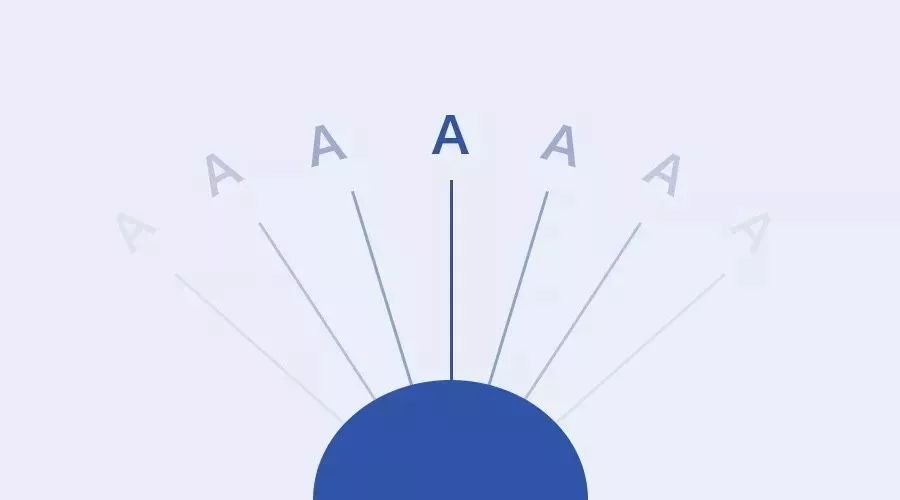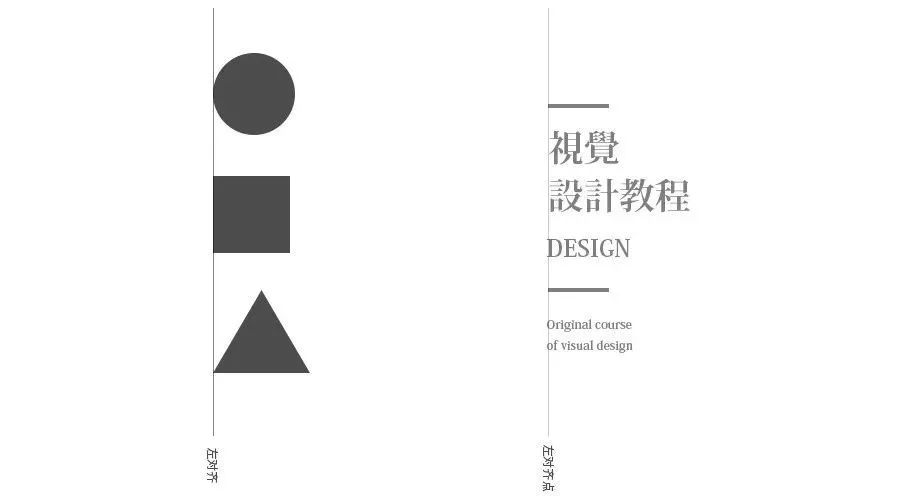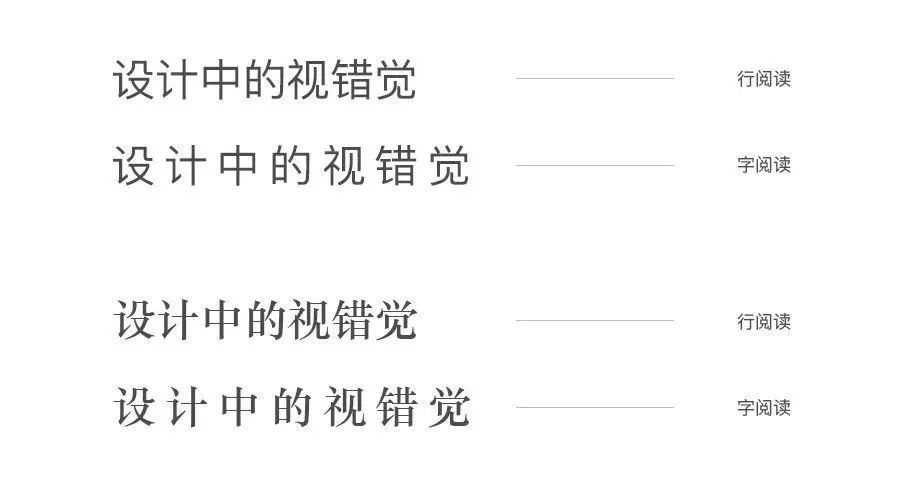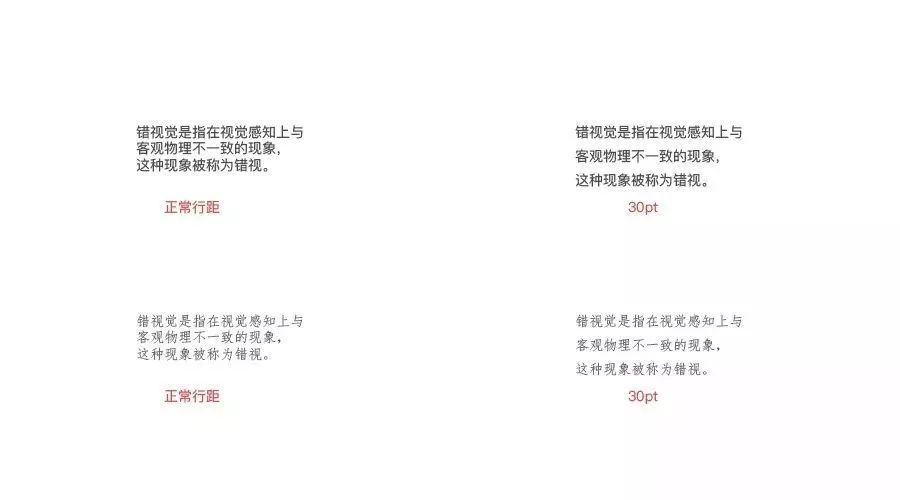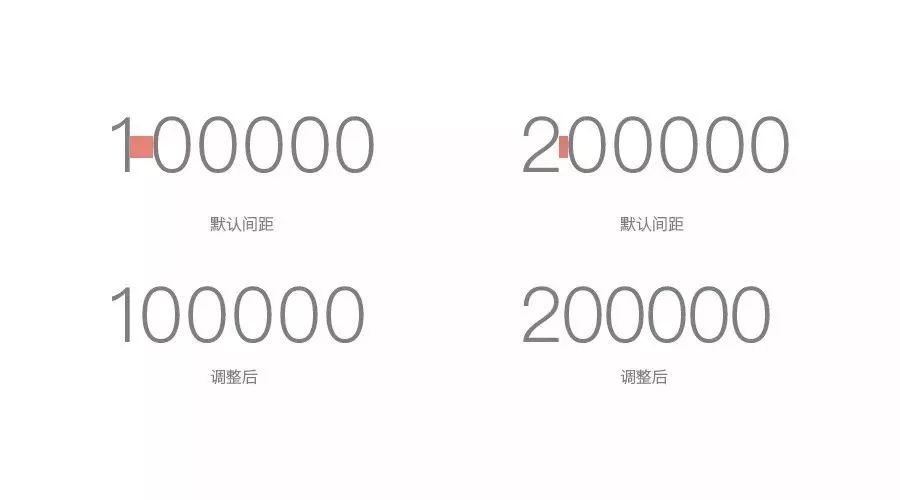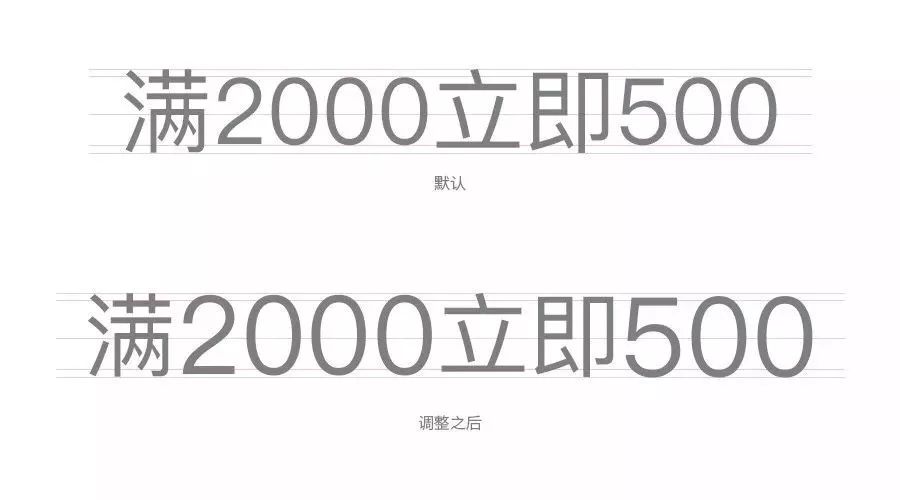
版式设计和字体设计中的人眼视错觉
什么是视错觉
视错觉是指在视觉感知上与客观物理不一致的现象,这种现象被称为错视。人的大脑在接受视觉系统传递而来的信息后,经过综合地进行对比和分析,会尽可能地做出正确的判断,但是,当信息不够充足或者错误收到干扰时,就会出现视觉上的形态与客观物理上的形态不一致的现象,也就会产生视错觉。
如图所示,正常情况下人眼对所看到事物的呈现,当人眼直视正前方的时候,只有中间位置的是最清楚的,而两边则是相对模糊的,同时也比较容易产生视错觉,而视错觉的原因除来自客观刺激本身特点的影响外,还有观察者生理上和心理上的原因。在设计中最常见的就是视觉方面的错觉,而错视觉对版式,字体的大小,间距等等都会有影响。
视错觉就是当人或动物观察物体时,基于经验主义或不当的参照形成的错误的判断和感知。在生活中我们也经常会见到一些视错觉的现象,而这些经典的视错觉也会经常被设计师应用到设计当中。
左边中间的线段与右边中间的线段是等长的,但看起来左边中间的线段比右边的要长,也称为缪勒—莱依尔(Müller Lyer)错觉。其原理是因为两边符号的方向变化,当两个符号的方向发生变化时,其视觉也会随之发生变化。
垂直线与水平线是等长的,但看起来垂直线比水平线长,也称为菲克(Fick)错觉;从视觉角度来讲时因为人眼的视觉中心点在竖线中间的位置,而横竖链接处容易给人一种一分为二的错觉,故在视觉感知上会认为竖比横线长。
中间的两个圆面积相等,但看起来左边中间的圆大于右边中间的圆;称为艾宾浩(Ebbinghaus)错觉。其原理是因为有不当的参照导致视觉感觉偏差,中心圆虽然是相同的大小,但由于外围参照物的对比,使得人眼在感知的时候发生了错觉。
在字体设计中,笔画通常会给我们这样三种不同的视觉感受,对于字体高级阶段来说,要尽可能的避免这样的视错觉感受,并考虑到这些习惯的阅读感知,进而对画面中的元素进行调整,避免视错觉的产生,以达到舒适阅读的效果。
在相同大小的两个纵向矩形中,按照视觉先左后右的观看顺序,当我们第一眼看到左边的矩形时会感觉比右边的要窄一些,这是因为人眼的第一感知通常要比最后的感知速度快当两个矩形放在一起时会有对比的心里,在视觉上会感觉左边的比右边的小一些,但实际上两个是相同大小的。
在同样大小的两个长方形中也会出现同样的问题,从视觉的感知来说,上面的要比下面的感觉细一些,颜色也要深一些。当,这种微妙的差距在设计中最普遍的存在,人眼的视觉中心通常会在两个长方形的中间靠下一些,对于上面的长方形视觉的感知稍微要弱一些,而下面的则感觉要重一些或者宽一些,颜色也会深一些,这些就是似错觉的感知,在设计中需要进行调整,尽量避免元素和字体的视觉偏差。
当两个大小的矩形横竖排列在一起时,横向的要比纵向的在视觉感知上面略宽一些,通常情况下横向的会给人一种厚重的感觉,而纵向的则是要偏瘦长一些,这也是心里感知的一种感知,最有特点的宋体就是经过这点的视觉调整,才有了较为舒适的横细竖粗的鲜明特点。
如图所示:在版式中经常会用到三种几何图形也存在一定的视觉差,经典的几何图形视错觉,由于形状的不同导致视觉面积的大小不一,在相同大小的情况下,矩形要比圆形和三角形的视觉面积大,矩形四周则是填充的比较满,而圆形和三角形四周都有相应的视觉留白,这种情况下就需要进行适当的调整。
把圆和三角形进行放大处理,规避掉圆和三角边缘的虚化空间,使其实际视觉面积与矩形大小保持一致,这种方式就是运用设计中的视错觉来营造相同大小的图形。
版式中的视觉差除了图形与图形之间,还存在于图形与之间,尤其是与宋体之间的视错觉最为严重;如上面案例所示,右边的线条与宋体在执行系统左对齐之后,通过观察会现,宋体字撇的视觉延伸与矩形之间,在视觉上看起来是没有对齐的,存在一定的视觉误差。
针对视错觉这一现象,我们需要从人眼感知的角度出发,对其进行适当的视觉修正,左边几何图形则是以矩形为基础,把圆和三角向左边移动,而右边案例则是把矩形向右移动,规避字体视觉延伸的误差。在设计中左右对齐的时候,一定要注意这些视错觉现象。
实际应用中的考究
人们在阅读的时候,尤其是看书的时候通常会有两种模式;一种是字阅读,另一种是行阅读;字阅读相对比较偏向在舒适悠闲的环境下进行阅读,而行阅读则是比较适合紧张快节奏的阅读行为,对文字而言,阅读的快慢均受字间距的影响,舒适的间距可以使用户看起来更加的轻松。案例如下:
快紧慢松
如图所示:除了宋体和黑体字体类型差别的影响之外,还有就是间距的问题。左边则是常规的字库默认的间距,而这个间距也不是唯一的标准,而是字体设计师在设计时所设的,不同类型的字体间距也不一样;在正常间距的情况下,比较适合行阅读;而右边的则是在常规的基础上放大了200,字与字之间的的空隙较大,给人喘息的机会,比较适合字阅读的方式。
不管是行阅读还是字阅读,行距同样也需要设计,可以根据不同的阅读方式设定相应大小的;左边为自动的行距,而右边则是设置成30pt的行距,对于人眼阅读的舒适性而言,右边则是比较好的。
案例解析
在设计中我们通常会把主标题的文字正常排列或者错乱的进行排列,但字与字之间的距离都不会太松散,这样处理有助于观者能够快速的了解所传达的信息,而放大字间距在画面中通常会当作说明性的文字或者修饰性的文字进行编排,对于主题来说则是进一步说明,通常是标题口号之类的词,案例如下:
新建一个画布,以几何图形为主视觉,表现视觉基因裂变的演讲公开课,考虑到视觉的裂变比较适合用抽象的几何元素,然后对几何主体进一步刻画;先对几何图形之行颜色叠加,选取相应的颜色,然后再对几何图形添加多层内阴影效果,需要注意里面的杂色和等高线的调整。
调整出最重想要的效果之后,接下来就是开始加文案信息来丰富画面的视觉效果以及所要传达的信息。为了表现出较强的视觉感,文字选择了一款日文字体与画面气质较为吻合,在正常的编排下,文字与几何图形存在一定的视错觉,以及文字间距也不是太理想,进一步调整:
通过对比可以看出,右边把文字的间距拉大了一些,并且把字体向下移动规避与几何图形的视错觉, 把字间距和行间距调整基本一致的效果,增加文字之间的空隙,使版面更加的舒适,信息传达更加有效;当然这也不是固定的,具体调整与否则要根据具体案例而定。另外,在版面的编排中,文字与元素的上边缘也是存在视错觉的,如上图案例中,文字的顶部要比元素顶部边缘低,但在视觉上看着是对齐的,创作时多注意视错觉的偏差细节,可以使画面更加的精致。
最终效果
在文字中最常见的视错觉就是中文和数字混合使用时,通常情况下中文都要比数字略大一些,当进行编排时需要注意调整数字或者文字的大小和重心,而有些字体在数字方面即使是默认的间距也会略大一些。在中文和数字的混合使用中,由于中文是以方块为基础的,而数字的字符均为细长,不适合用方块的标准去做,通常会以英文的标准开发,所以数字通常都会比中文要小一些,但视觉重心是不变的;在设计中也是通常会被忽略的细节之一。
以常用的苹方黑体为例,在使用默认常规的间距情况下,数字1和0之间的间距过大,这个时候如果需要使用默认的间距时,则需要调整1和0之间的间距;而2和0之间的间距则属于正常,但整体感觉也会过于松散,当把间距进行缩小-50的时候,相对来说在视觉上则要比默认的间距更加舒适一些其原因主要是因为中文以田字格为设计基础的原因导致,在使用时一定要注意调整,以达到视觉平衡的效果,避免软件默认的常规而忽略了人眼的视错觉,进而影响人眼阅读的舒适度。
如上图所示:以苹方字体为例,在正常的输入中文和数字之后,数字以重心线为基础,上下的边距则要比中文的小一些,有点萎缩的感觉,看上起不太舒服;而经过调整之后的一组字,则是增加了视错觉,并以视错觉的方式呈现出来,在视觉上看着是一样大小,其实数字要则要比中文大了一些,而且也略粗了一些;需要注意的就是在调整的时候,一定要按照重心线调整,切记要与上下边距对齐。
如案例所示,在电商中或者金融行业中经常会遇到文字和金额的组合,左边的文字和数字都是字库默认的间距,由于字体的原因整体看上去间距稍微有点大,而数字也比文字要小一些,然后利用视错觉进行调整。
可以直接选中单独的数字进行放大,但切忌放大之后数字的视觉中心会向上,这个时候需要向下调整-2px已达到视觉的平衡;另外也可以重新建立文本框调整到合适的大小即可。
如案例所示,在电商或者金融行业中经常会遇到文字和金额的组合,左边的文字和数字都是字库默认的间距,由于字体的原因整体看上去间距稍微有点大,而数字也比文字要小一些,然后利用视错觉进行调整。调整之后的文字信息看上去更加的紧凑,而数字与中文在视觉上的大小也基本保持一致,但实际上整体的间距是缩小了一些,数字也放大了一些,以重心线为基础,顶部与中文是一致的,底部则要比中文高一些,整体看过去更加的舒适,由于是广告投放图,可以是观者更加快速的了解信息,给观者一种紧迫感;调整的方法不限,可根据自己的习惯进行操作。
在字体设计中最常见的就是笔画的粗细问题,如中文宋体类型的字体就是最经典的案例,横竖同存的字体中,人眼通常会感觉横笔较粗,故在宋体类型的字体中规避了视错觉的问题,所以现在的字体设计通常会把横细竖粗当作专业术语来讲,与人眼的第一感知则是相反感觉。
如图所示:当我们把横细竖粗的特点换成横粗竖细的形式之后,从案例中可以看出,视觉较重的横笔感觉更加粗壮;右边则是横细竖粗的宋体特点,在弱化视觉较粗的横之后效果更加的舒适。当然这种方式也不是固定的,需要根据不同的结构进行细微的调整。
在字体设计中使用相同粗细的笔画营造粗壮有力的感觉时,横笔往往会感觉更加的厚重,而竖笔则会显得细一些,为了规避这种笔画的视错觉则需要把横笔做相应的调整。
把横笔相应的缩小4px或者6px,减小横笔的视觉厚重感,使其在视觉上与横笔保持一致,这样看起来会让字体更加舒适。
还有一种情况就是,当点遇见横,或者是进行创意的设计时也需要注意点与横的视错觉。
如果所示:两组案例看起来没有什么差别,仔细观察会发现上面的“创”字比下面的“创”字扁一些,同时与左右两个字的点相比则显的高一些,这是因为当横笔与点相遇时,由于点的视觉面积较小,而横和竖则大一些,在视觉上会显得横竖更高一些,这时就需要调整一下在视觉上的平衡。
把两组案例重叠之后,用不同颜色展示之后会看出明显的差别,黑色的创字要比其他两个字的顶部高出1-2px左右。
总结
在字体设计中,视错觉通常会出现在宋体类型的字体中,多横多竖的字体中,以及字体的点、撇捺与横竖之间,而版式则是与字体的选择与几何图形的关系中,以及几何图形之间的关系中。设计中的视错觉大多也都是生活中经常存在的一些视觉现象。大家多以发现的眼光看待问题,多尝试,在设计中巧妙地利用可以营造出非常棒的设计作品,但同时也需要注意调整普遍存在的视错觉现象来优化自己的设计作品,把控好细节才能提升作品的精致度。